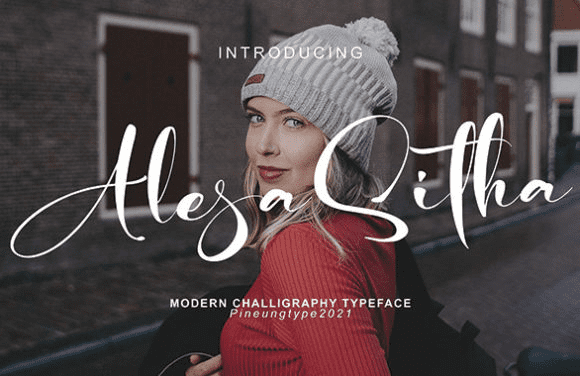
Название: Alesa Sitha Font (2021)
Alesa Sitha - это изысканный шрифт, выполненный в каллиграфическом стиле.
Он идеально подходит для проектов, которым нужна аутентичная атмосфера и стильный, дорогой вид!
Название: Alesa Sitha Font (2021)
Alesa Sitha - это изысканный шрифт, выполненный в каллиграфическом стиле.
Он идеально подходит для проектов, которым нужна аутентичная атмосфера и стильный, дорогой вид!